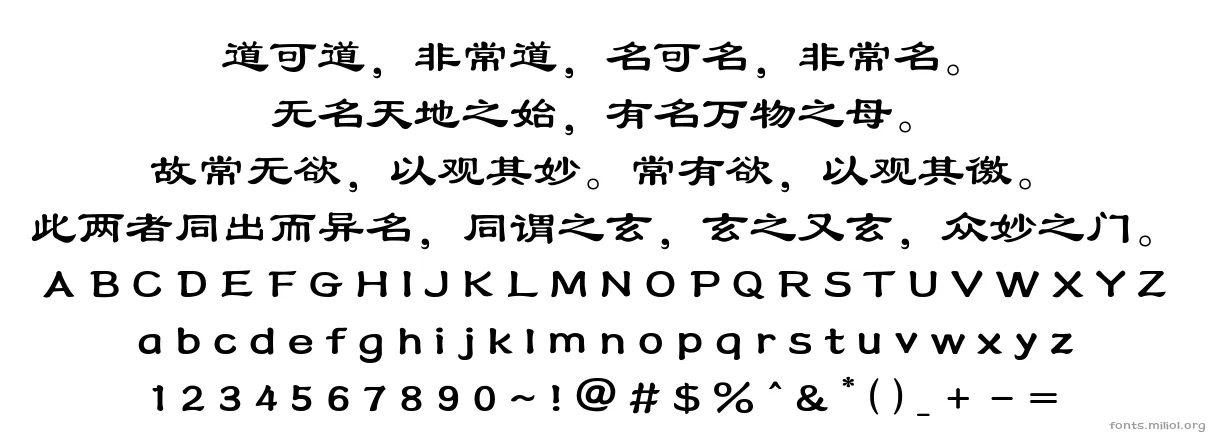
方正隶书_GBK (FZLiShu-S01) (FZLSK--GBK1-0) 字体下载
**方正隶书_GBK字体简介**
方正隶书_GBK(FZLiShu-S01)是一款经典的中文印刷字体,隶属于方正字库的GBK编码系列。该字体以传统隶书为基础,笔画浑厚端庄,兼具古朴韵味与现代设计感,适用于标题、广告、书籍装帧等场景。其GBK编码支持包括简体、繁体及生僻字在内的两万多个汉字字符,兼容性广泛。
作为一款标准化的商业字体,方正隶书_GBK在保留隶书“蚕头燕尾”特征的同时,优化了结构比例,确保屏幕显示与印刷输出的清晰度。字体线条流畅,庄重而不失灵动,适合文化类、传统节日或品牌宣传等主题设计。